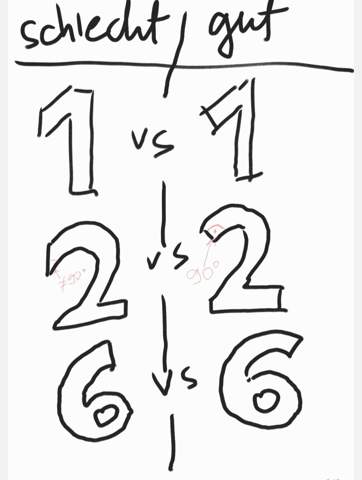
Wie heißt die Schriftart von L'Oréal?
Ich meine die Schriftart wie wir die im ersten Bild sehen. Was ich schön finde ist dass die serifenlos ist und die Linie quasi immer im 90 Grad Winkel abgeschnitten wird. Ich frage mich wo man solche Schriftarten noch finden kann zum runter laden (gesucht habe ich schon ohne Erfolg).
Kennt ihr vllt. auch ähnliche Schriftarten?
Hier nochmal ein Bild in dem ersichtlich wird was ich meine:
Spontan fallen mir die Syntax und die Officina Sans ein.
Wenn du einen Pc hast Versuch es mal mit Arial Black
Ich denke mal schon, dass die Antwort ernst gemeint ist, denn Arial Black wäre durchaus eine passende Alternative, wenn auch nicht 100%-ig deckungsgleich.
Comic Sans MS
Ich hoffe deine Antwort ist nicht ernst gemeint